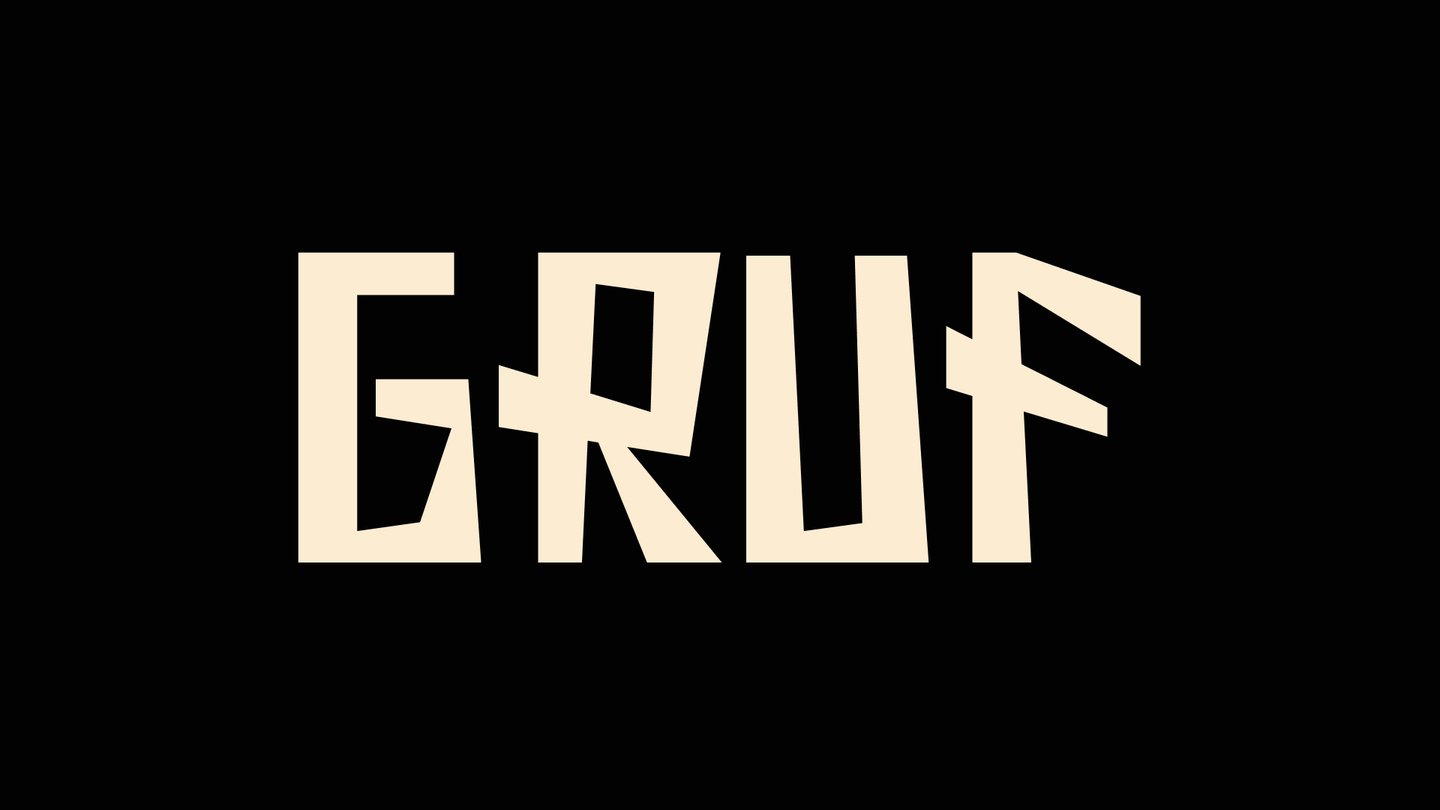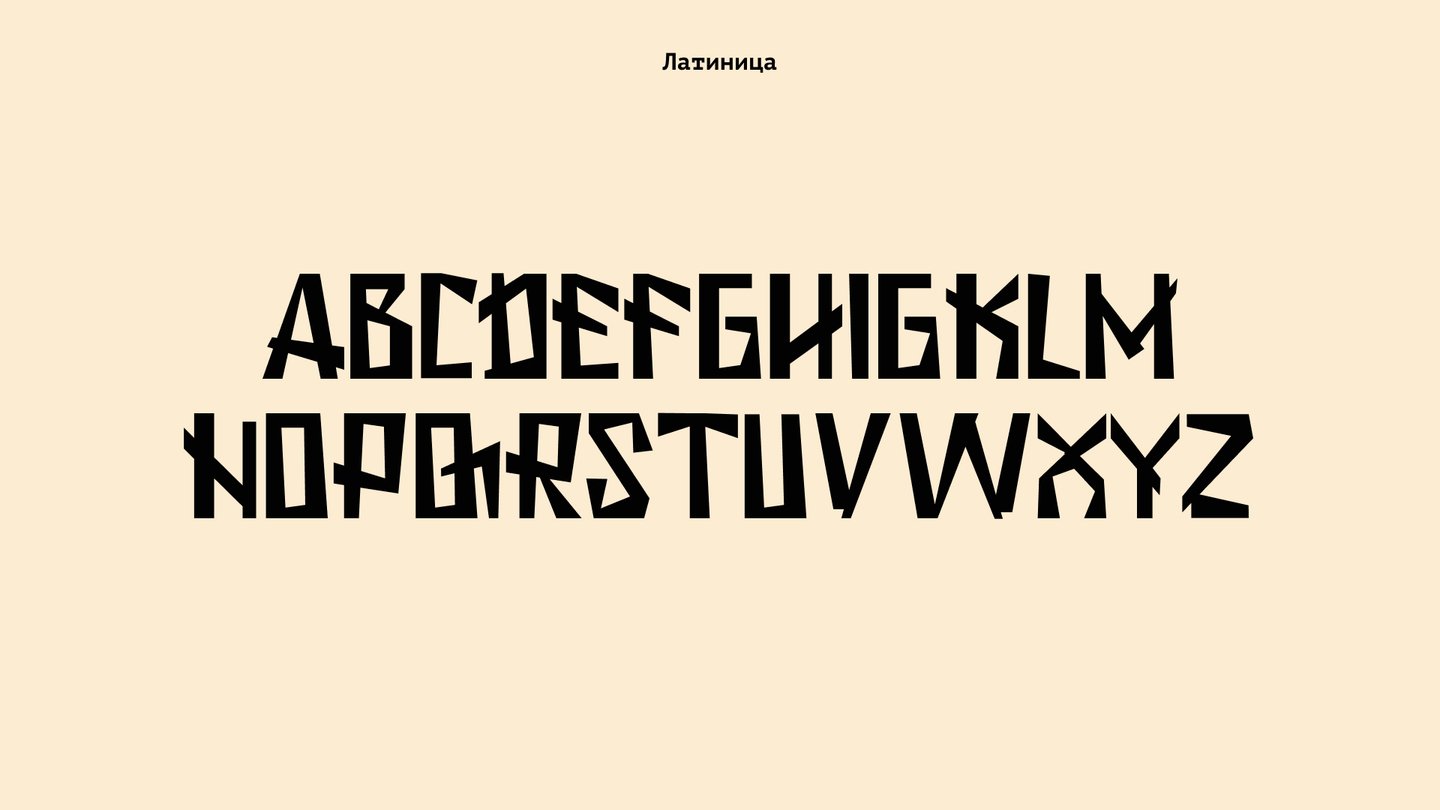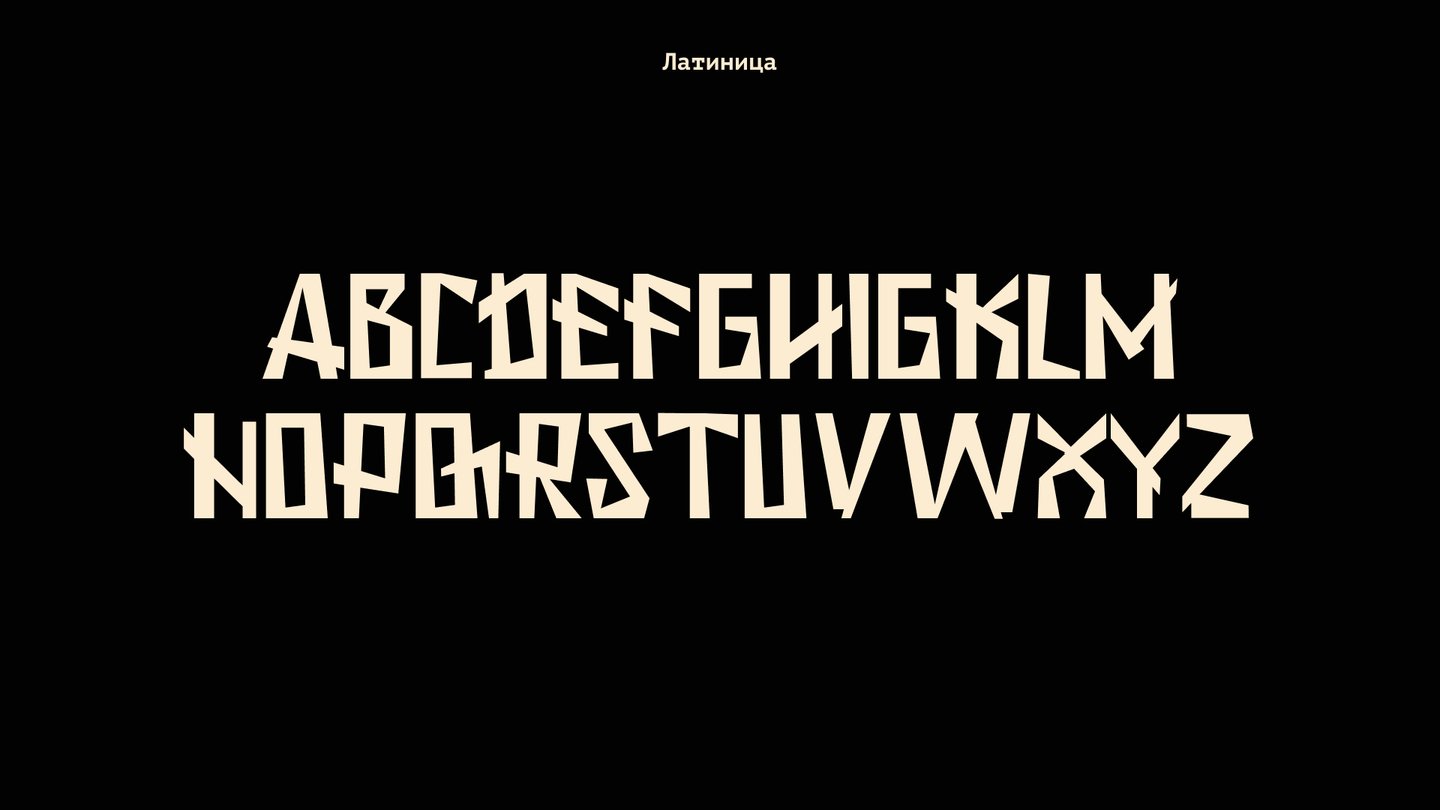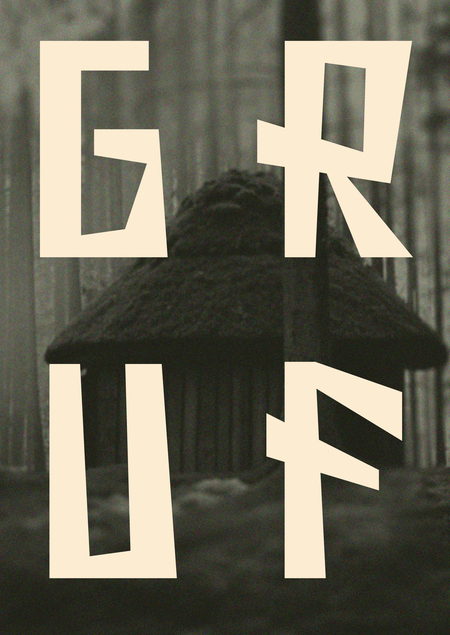
GRUF — палочный шрифт, вдохновленный кельтскими рунами, тёмными сказками, славянский мифологией и культурой видеоигр. Сам шрифт с ломаной геометрией выглядит как последовательность магических знаков за счёт острых диагоналей и рубленных концов.